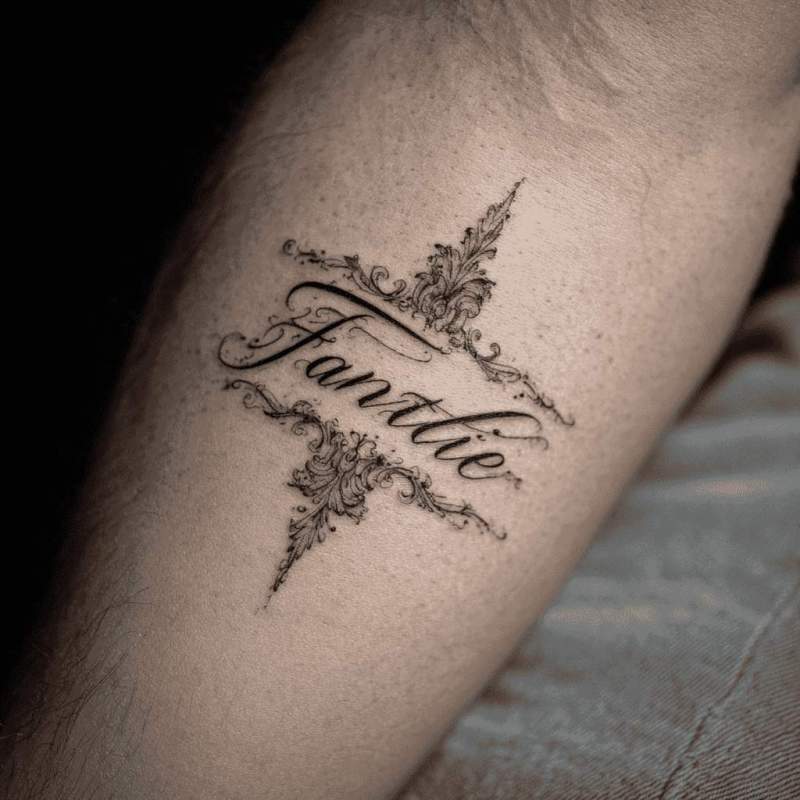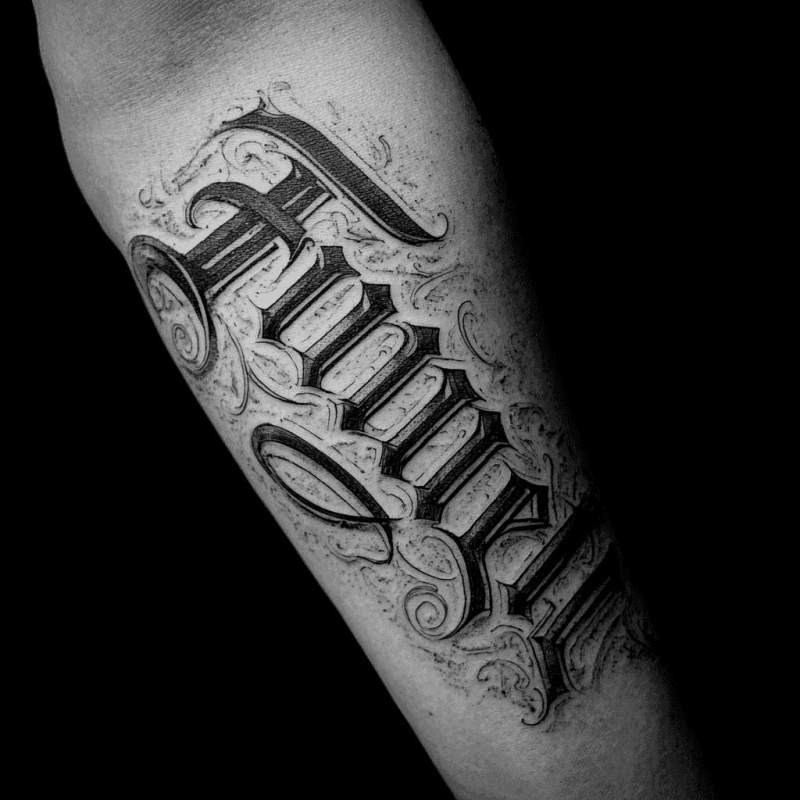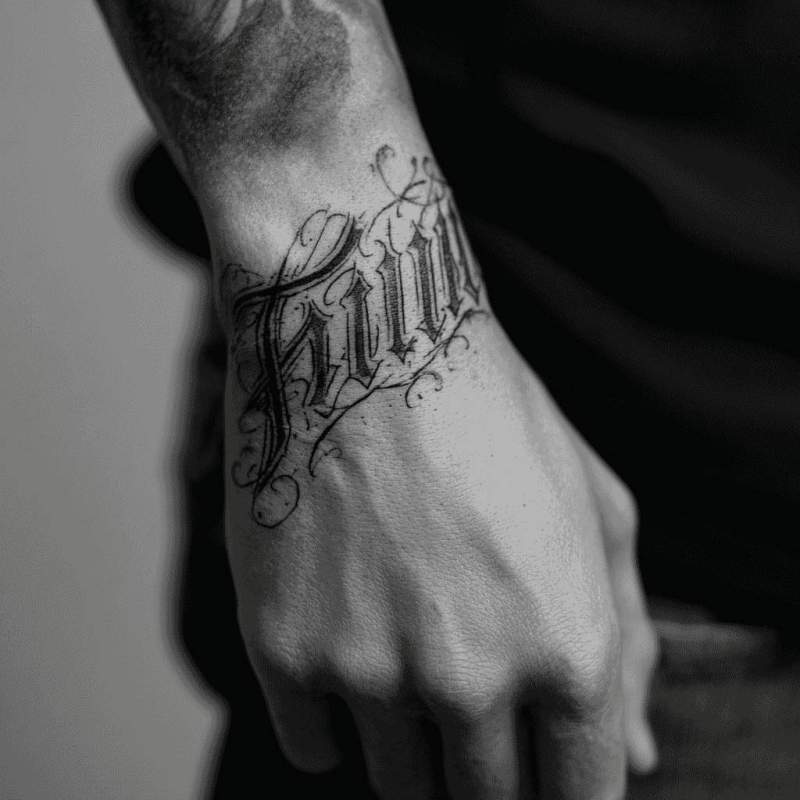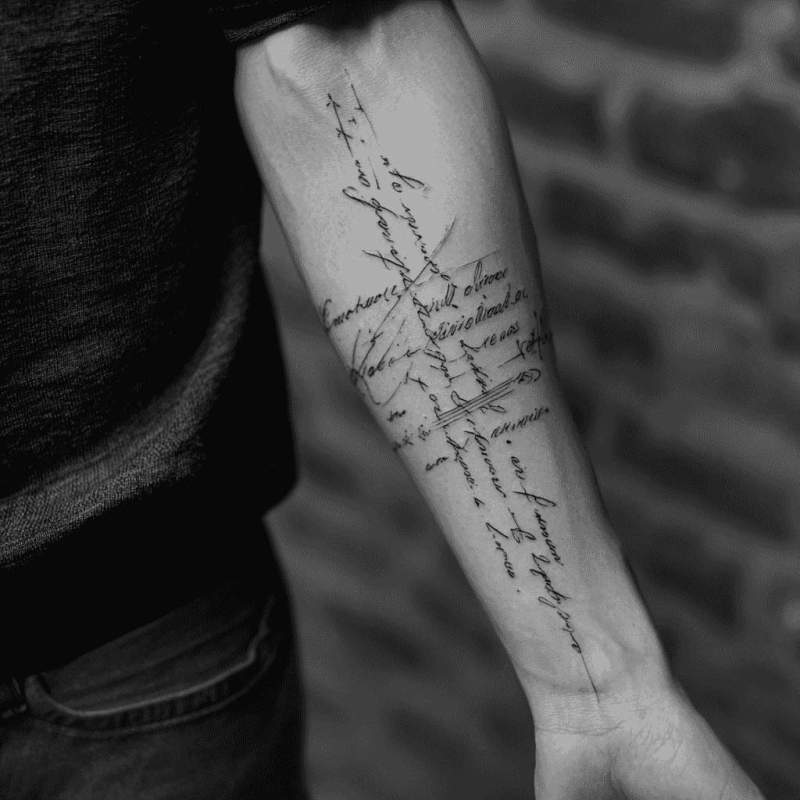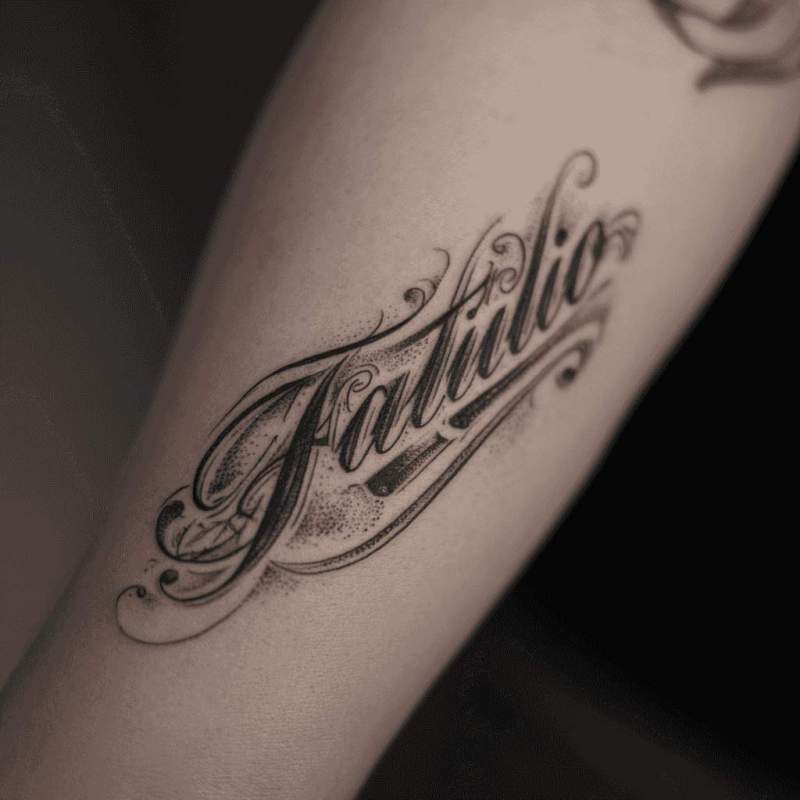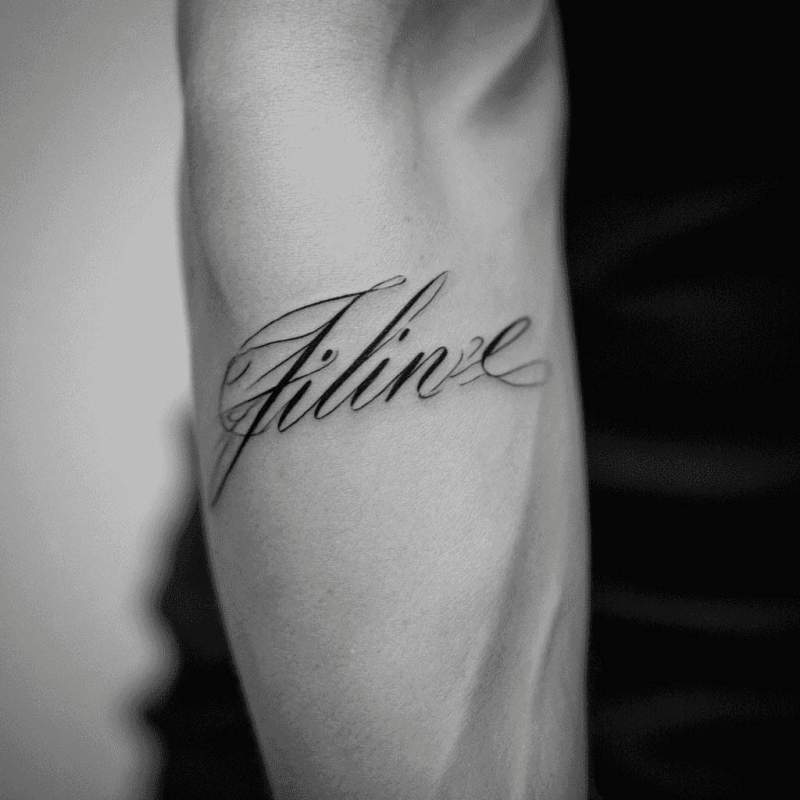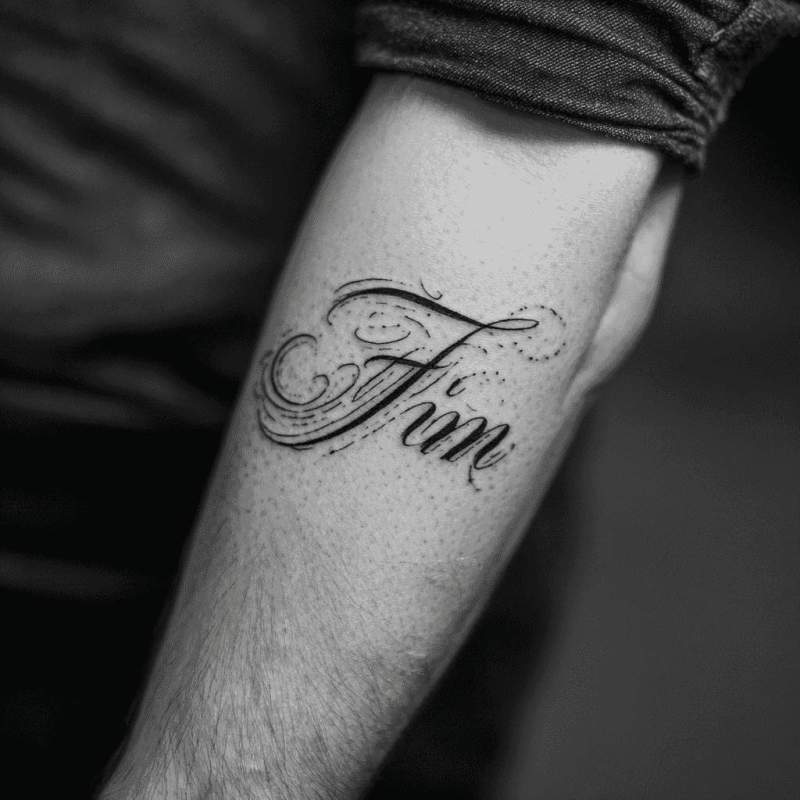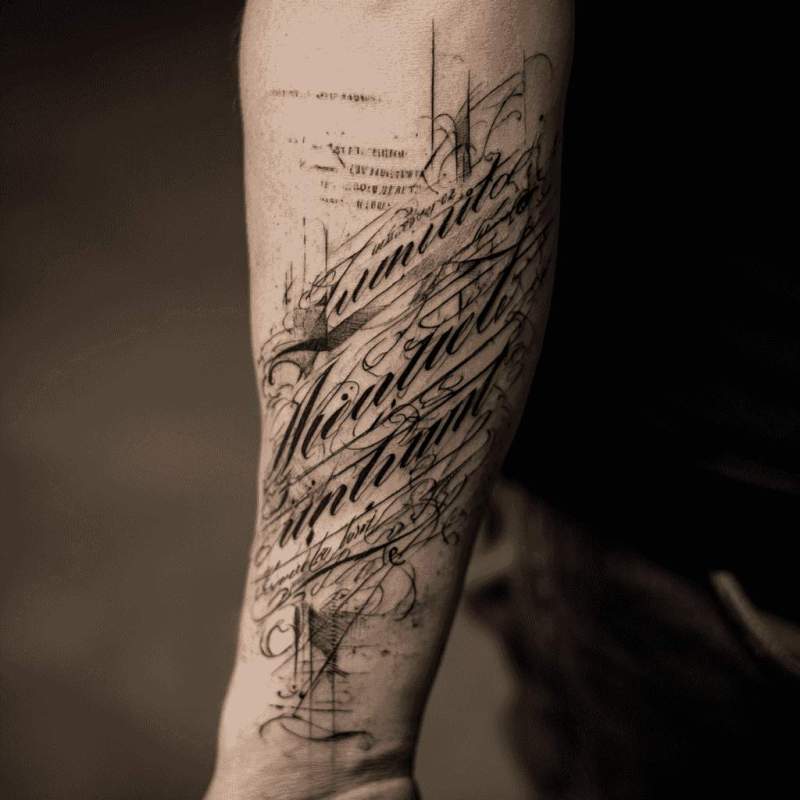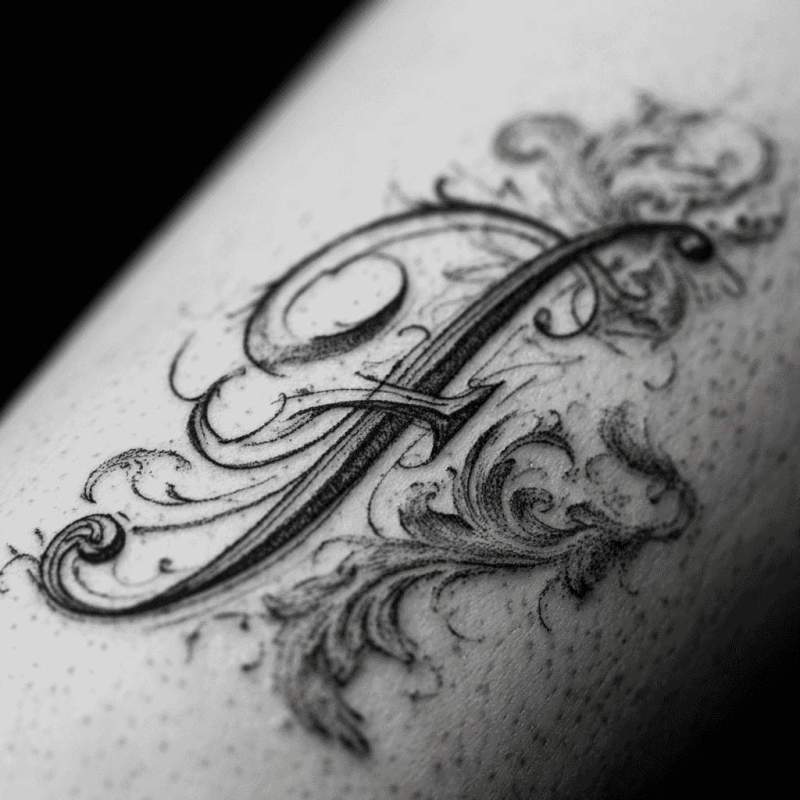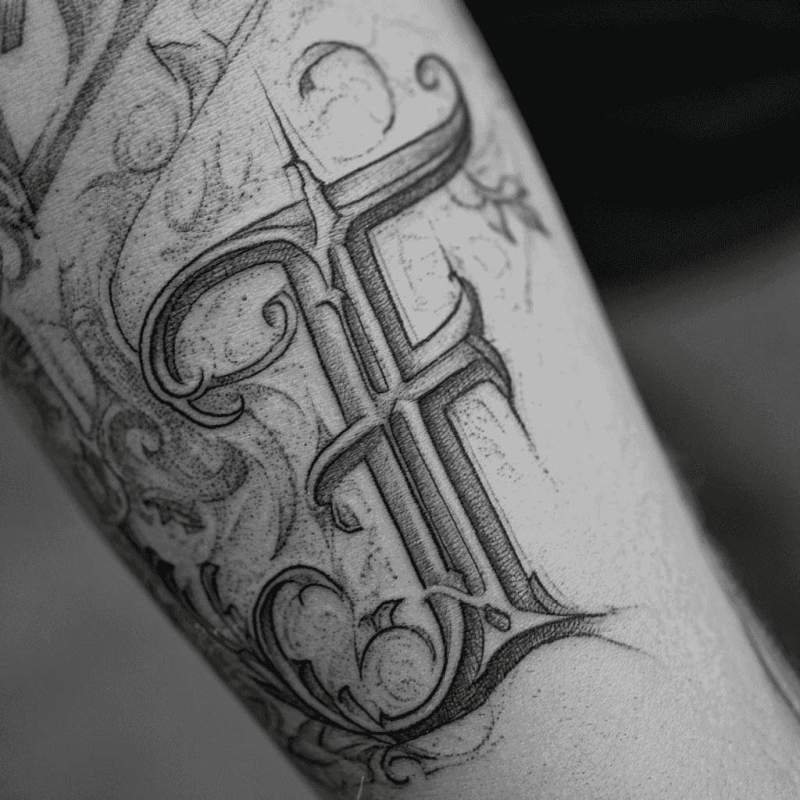
Die besten Tattoo Schriftarten Fineline Designs in Schweiz (2025)
Schreibst du mit feinen Linien? Die Typography-Fineline-Tattoo-Meister von Lebende Legend Tattoo in Bern, Schweiz haben die besten Schriftarten in Feinlinien-Technik kuratiert, um dir elegante Text-Inspiration zu entfachen.
Was sollte man ΓΌber die Bedeutung von einem tattoo schriftarten fineline wissen?
Typografische PrΓ€zision zeichnet sich in Fineline-Schriftarten-TΓ€towierungen durch dΓΌnne, elegante Buchstaben. Kalligrafische Kunstwerke und moderne Typografie vereinen sich in diesen Designs. Verschiedene Schriftarten und GrΓΆΓen ermΓΆglichen individuelle Text-Kunstwerke.